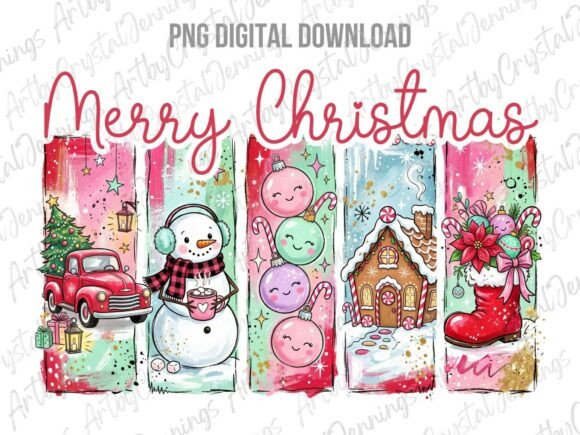
Merry Christmas Holiday Brushstroke PNG
Att hitta rätt designelement kan vara utmanande, men Merry Christmas Holiday Brushstroke PNG erbjuder en exceptionell samling som omedelbart lyfter ditt arbete.